Ipiranga: Gerando valor para a marca através da tipografia
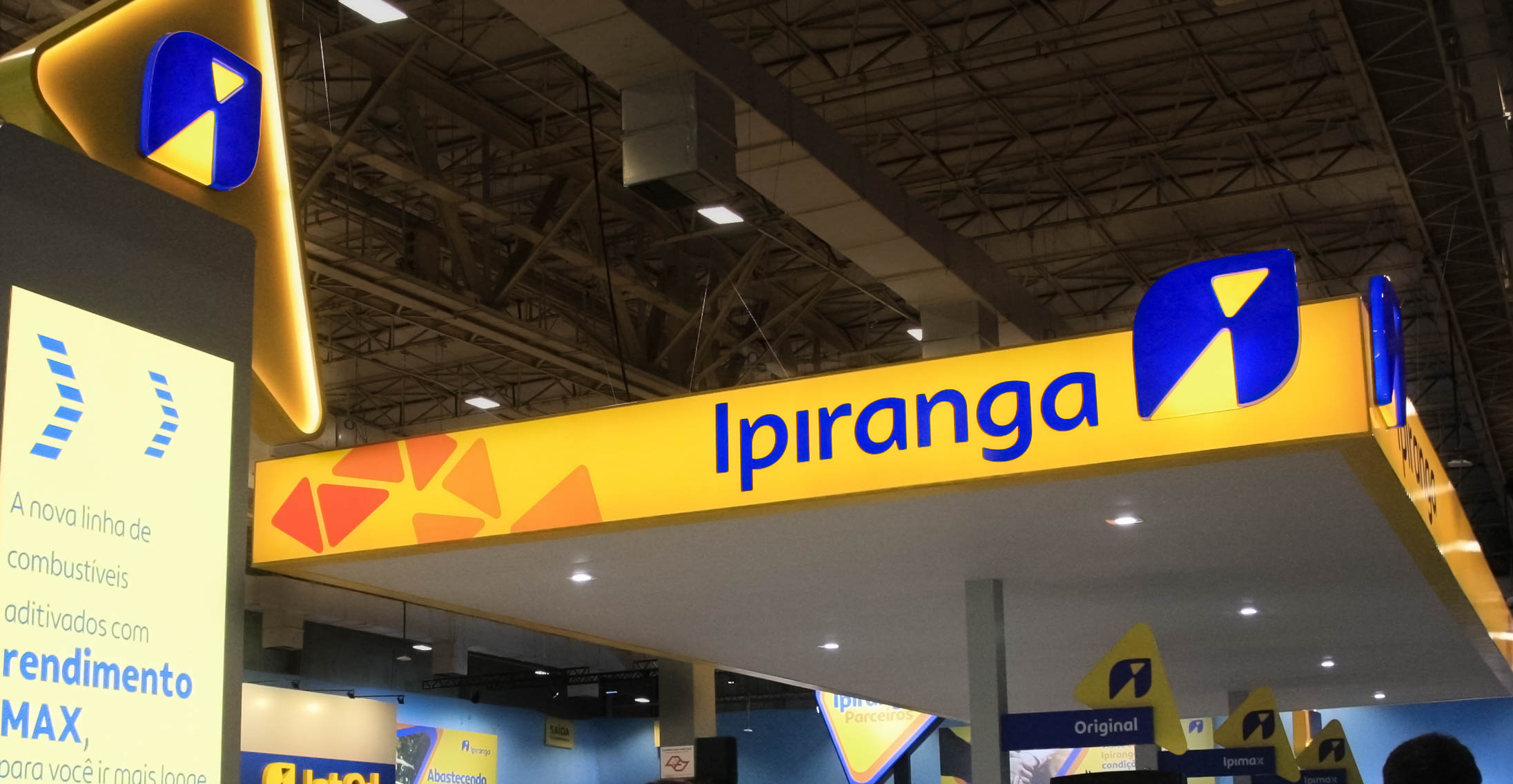
A Ipiranga reposicionou sua marca para oferecer uma nova proposta de experiência para os consumidores nos postos da rede. Com o novo propósito de “abastecer a vida em movimento”, a companhia quer estar presente nas diversas jornadas de mobilidade das pessoas. A convite da Superunion, pegamos carona e auxiliamos neste processo, onde atuamos no novo logotipo e na criação de uma fonte sob medida, exclusiva.
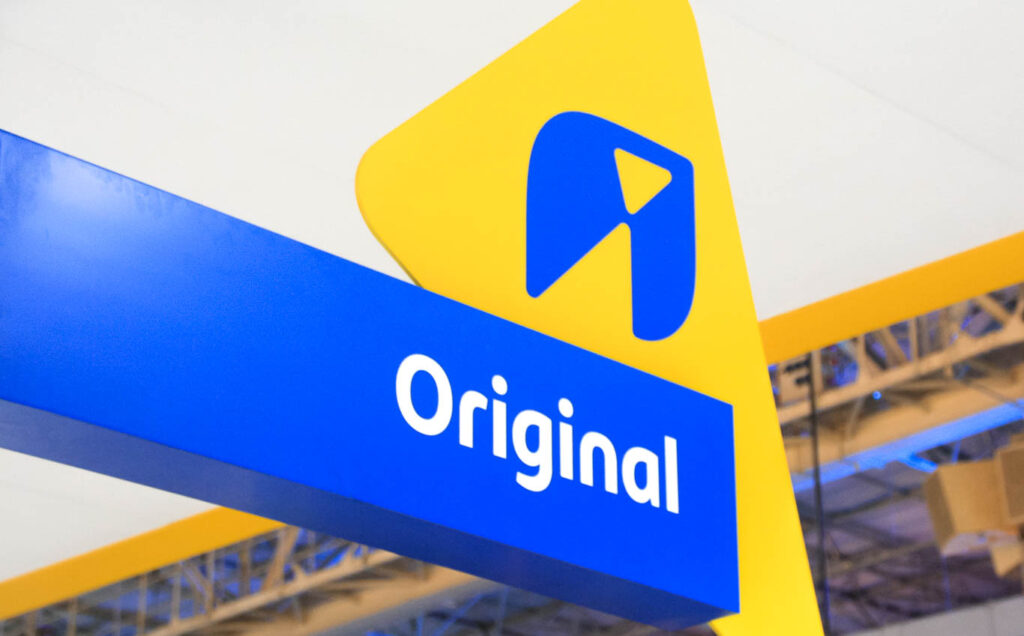
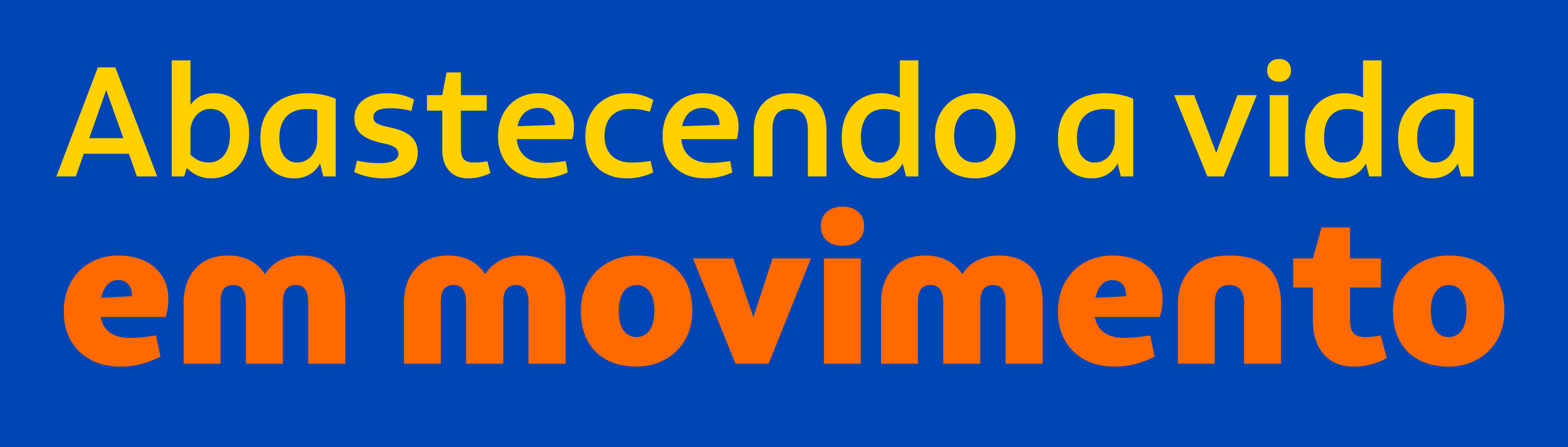
Para conectar a tipografia com o design e o negócio de Ipiranga, iniciamos com nosso workshop, mapeando com a Superunion e representantes de diversas áreas da Ipiranga, a estrada que teríamos pela frente, os desafios e nosso destino final. Iluminamos as oportunidades de melhorias relacionadas ao uso das antigas tipografias, mapeamos a personalidade da marca em termos tipográficos, descobrimos como estes conceitos são traduzidos em formas visuais pela Ipiranga, além de acordar os critérios de sucesso do projeto.
Com este roteiro bem alinhado, a viagem se revelou um passeio. A personalidade da nova tipografia precisava ser humana, com um toque de descontração. Ter ousadia na medida certa para, com o tempo, gerar reconhecimento de marca: ao ler uma palavra, o Brasil saberia que é a Ipiranga falando. Para isso, a unidade visual em todas as manifestações é vital — seja no cardápio da padaria da AmPm, no preço do combustível, até os posts em redes sociais ou placas publicitárias em campos de futebol. Ou seja, a tipografia precisava ser versátil e funcionar bem em diversas situações.
Na apresentação de 12 ideias tipográficas, onde a Ipiranga poderia escolher duas para avançar no projeto, a empresa foi certeira. Uma ideia chamou a atenção de todos e entregou tudo o que era preciso. Seguimos o caminho com segurança.
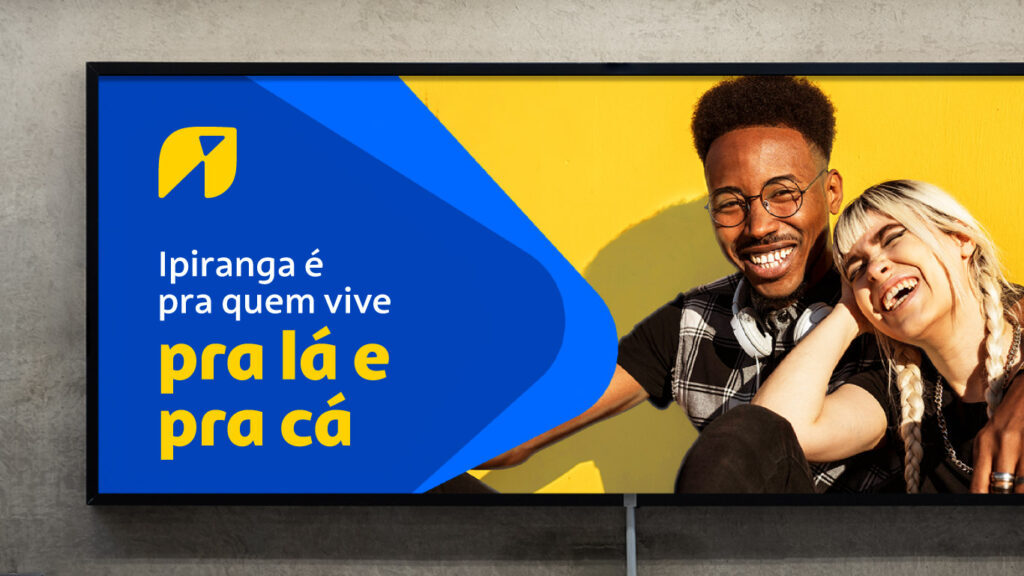
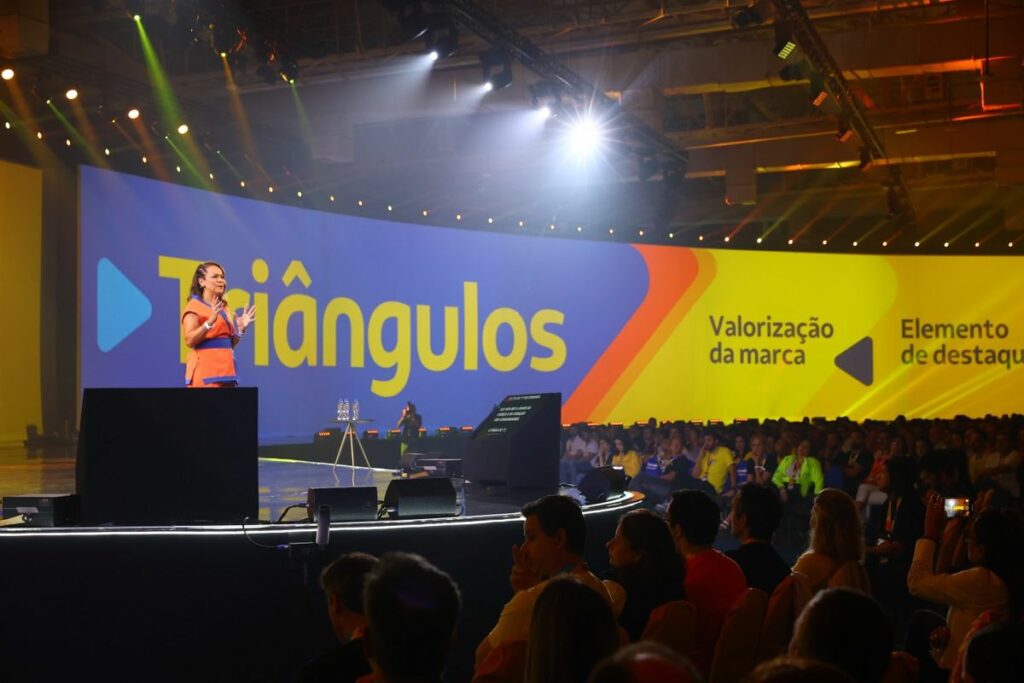
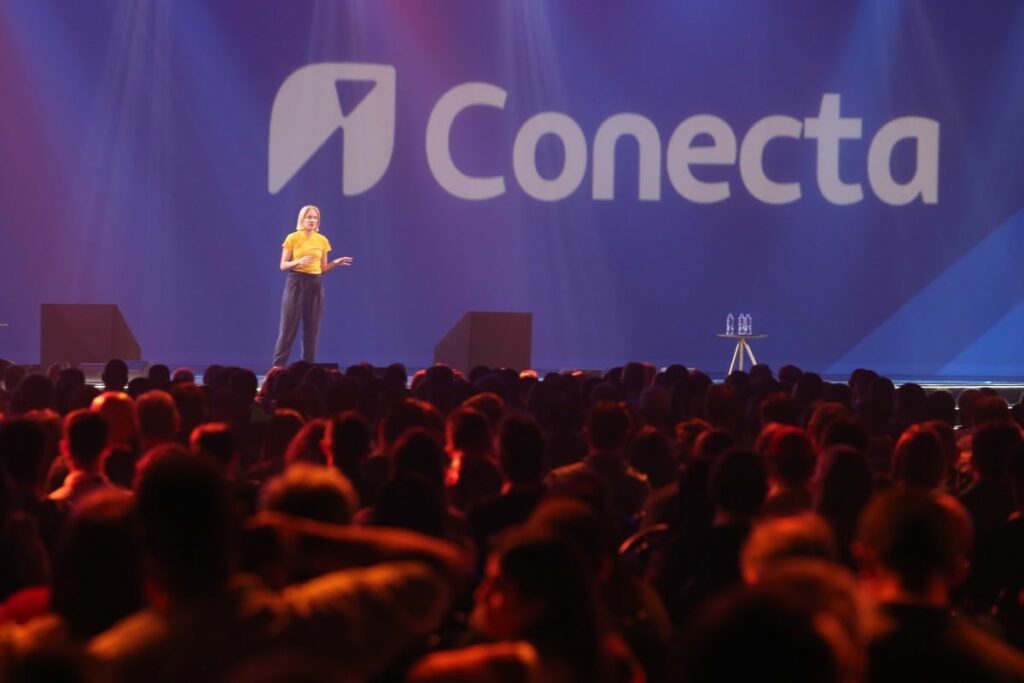
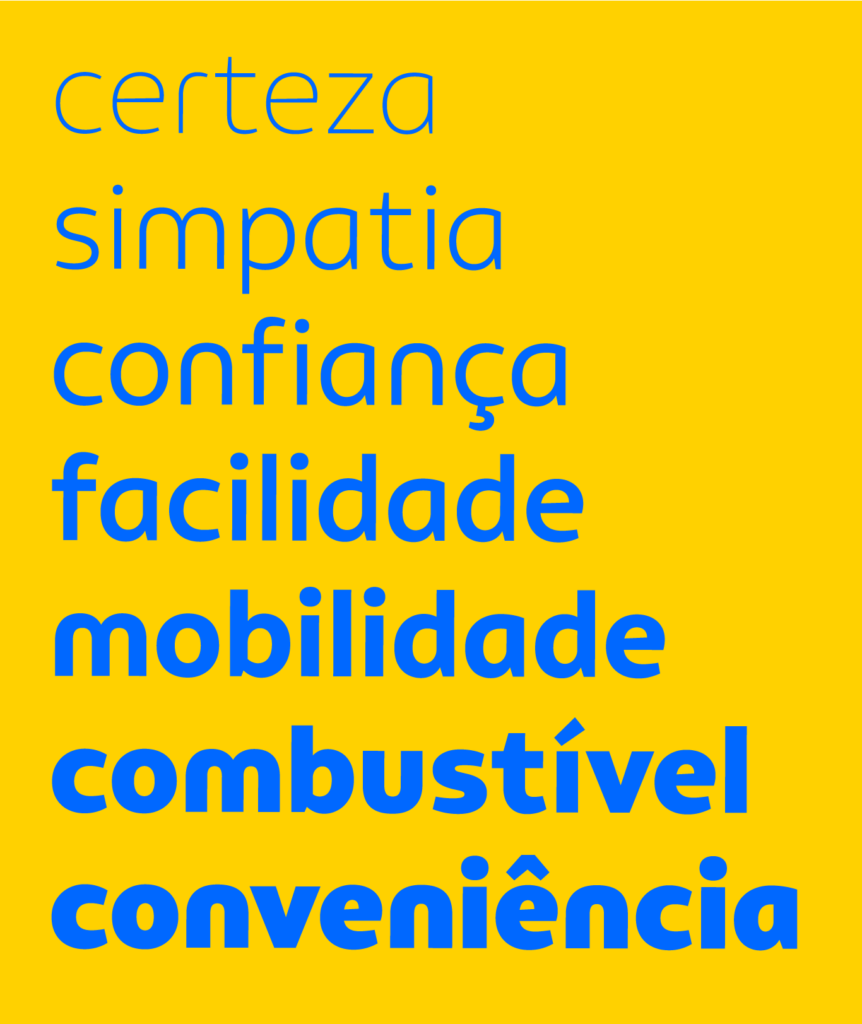
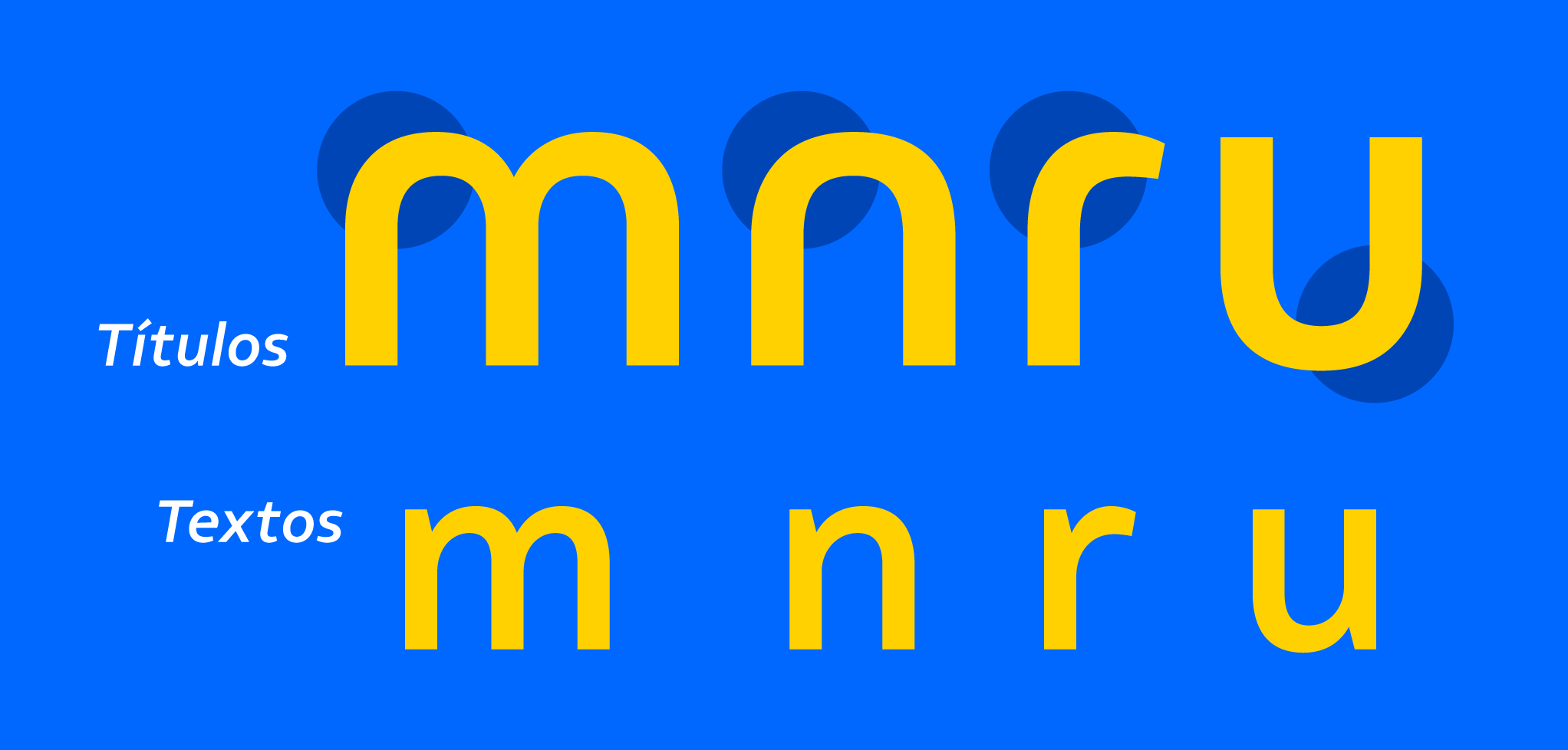
A construção simplificada, sem esporas nas letras ‘m’, ’n’, ‘r’ e ‘u’, salta aos olhos e revela uma certa informalidade e praticidade. As terminações afinando revelam uma diferença de espessura entre traços grossos e finos, resultado da gestualidade da caligrafia, um forte elemento humano. A construção bastante aberta de letras como ‘c’, ‘e’, ‘r’ e ’s’ facilita a legibilidade em tamanhos pequenos, assim como a nitidez na renderização em dispositivos digitais.
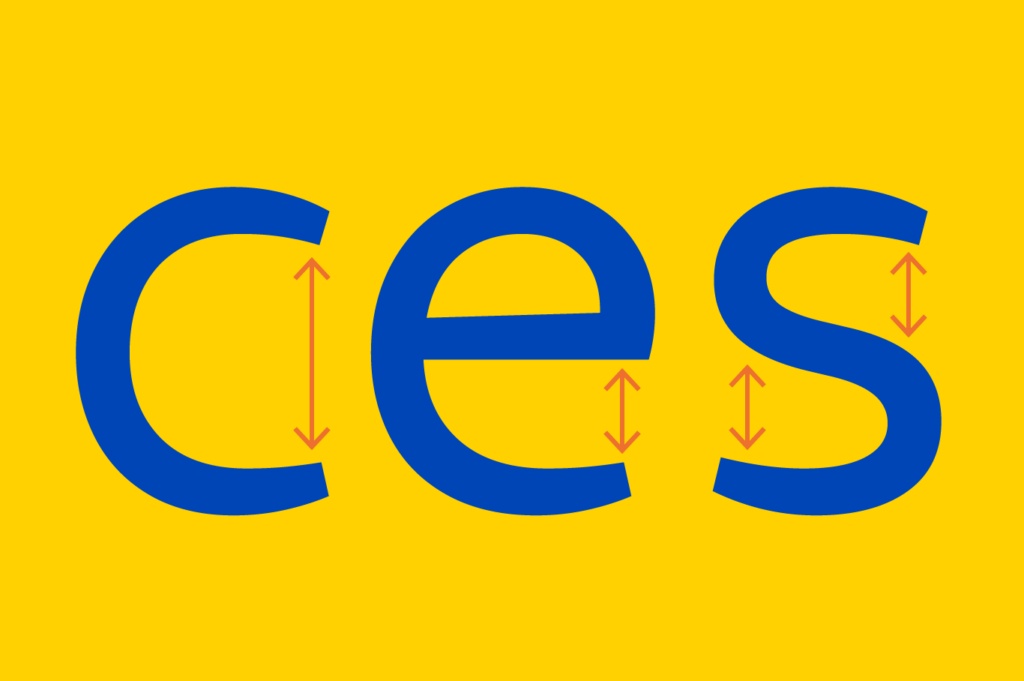
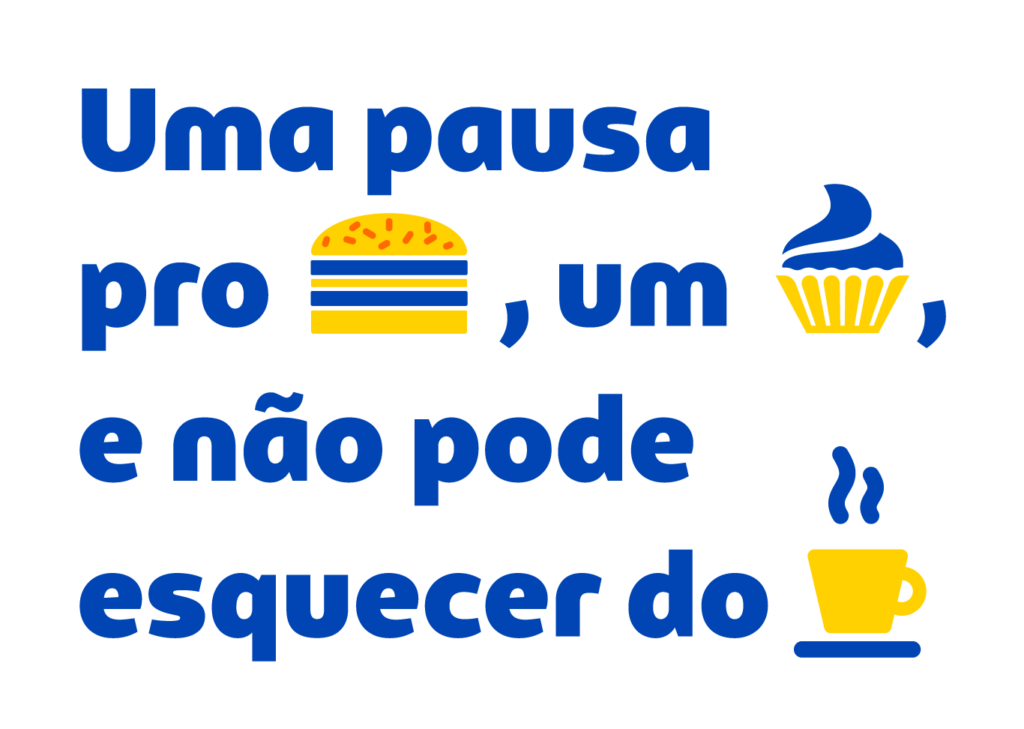
A expressividade e legibilidade são balanceadas com precisão através de duas versões da tipografia: Títulos e Textos. Nesta última, como a prioridade é a legibilidade e acessibilidade, as letras ‘m’, ’n’, ‘r’ e ‘u’ ganham esporas numa construção mais convencional. Enquanto na tipografia Títulos a letra ‘a’ acelera o processo de gerar reconhecimento ao replicar a forma presente no logotipo, na versão Textos ela tem um desenho mais legível, o distanciando de outras letras redondas.
Agora, cada palavra escrita pela Ipiranga é uma oportunidade de acelerar o processo de diferenciação de sua imagem, com segurança, e gerar valor para a marca.